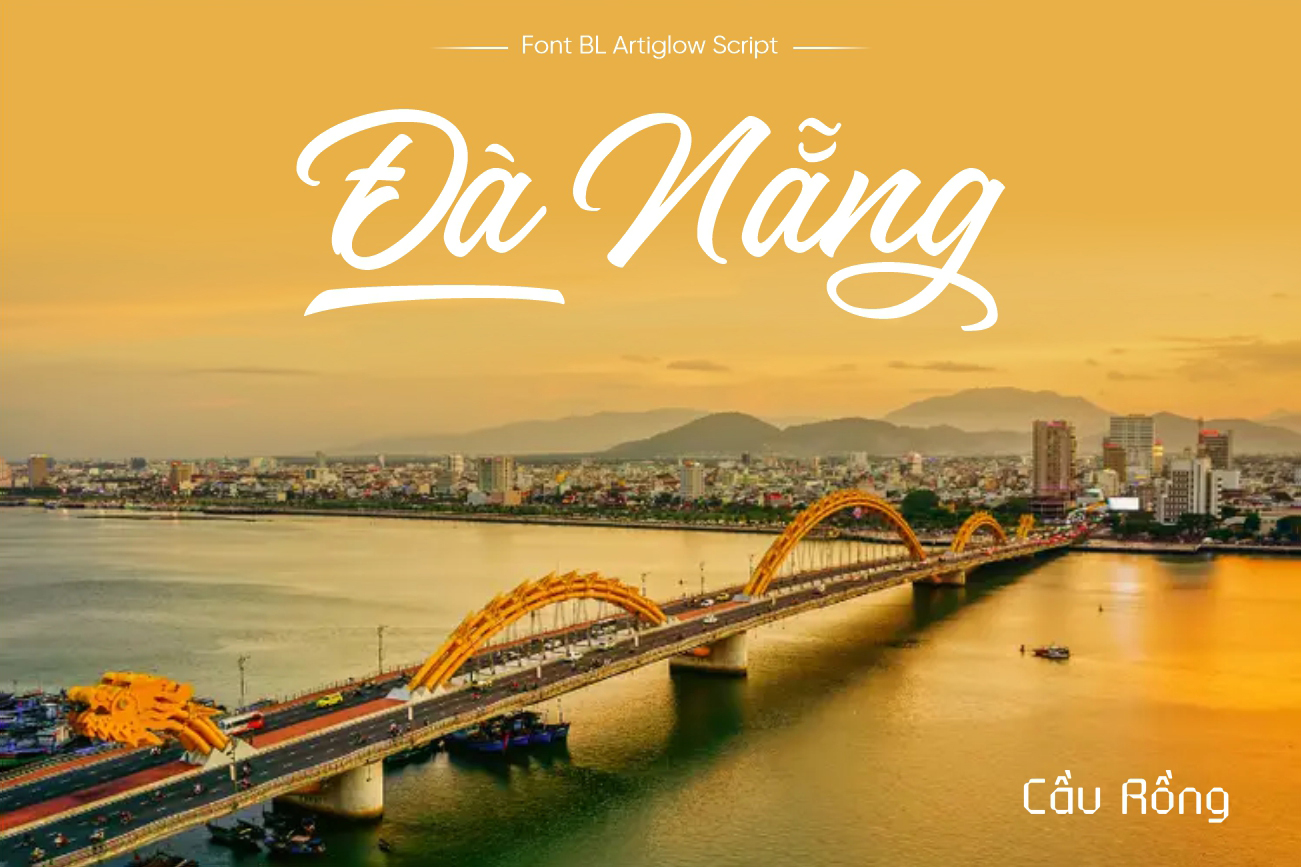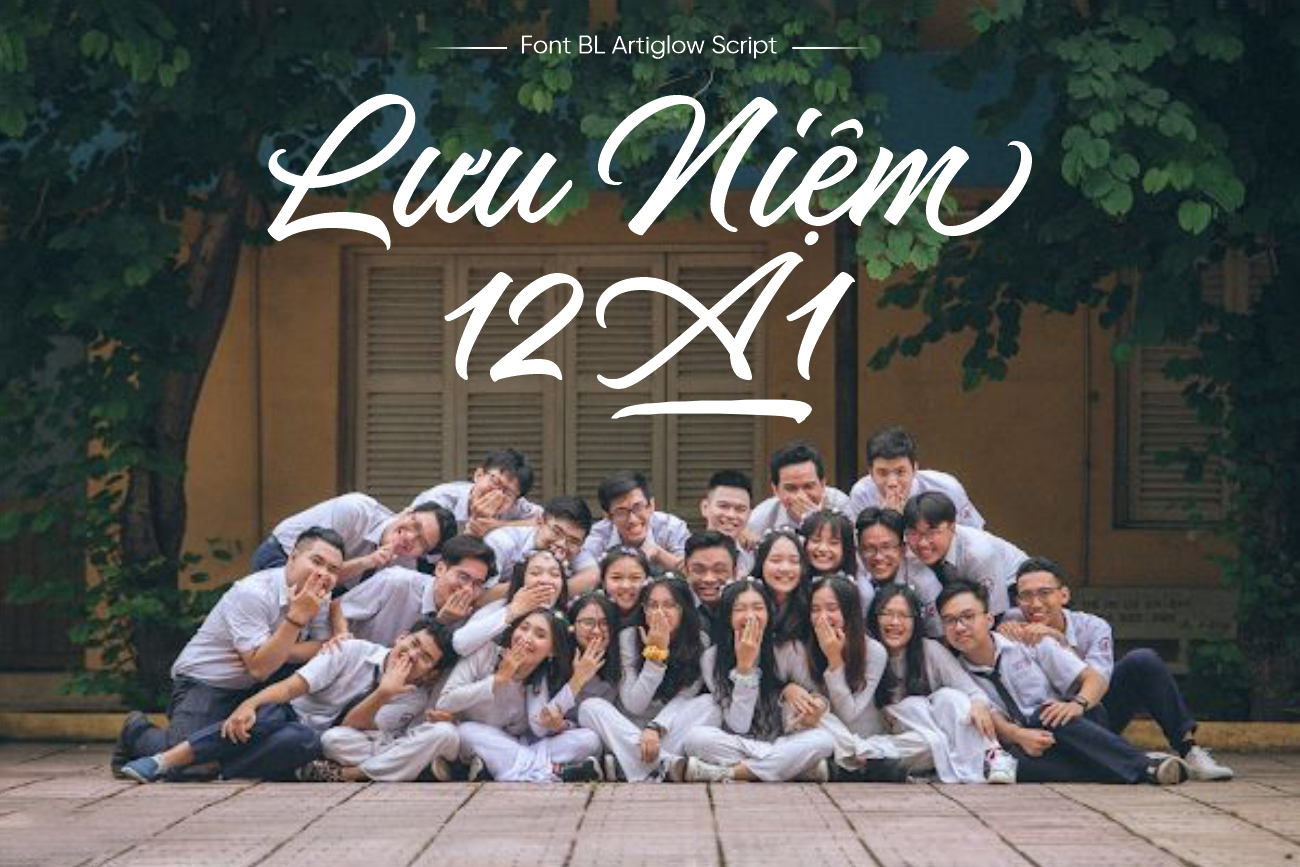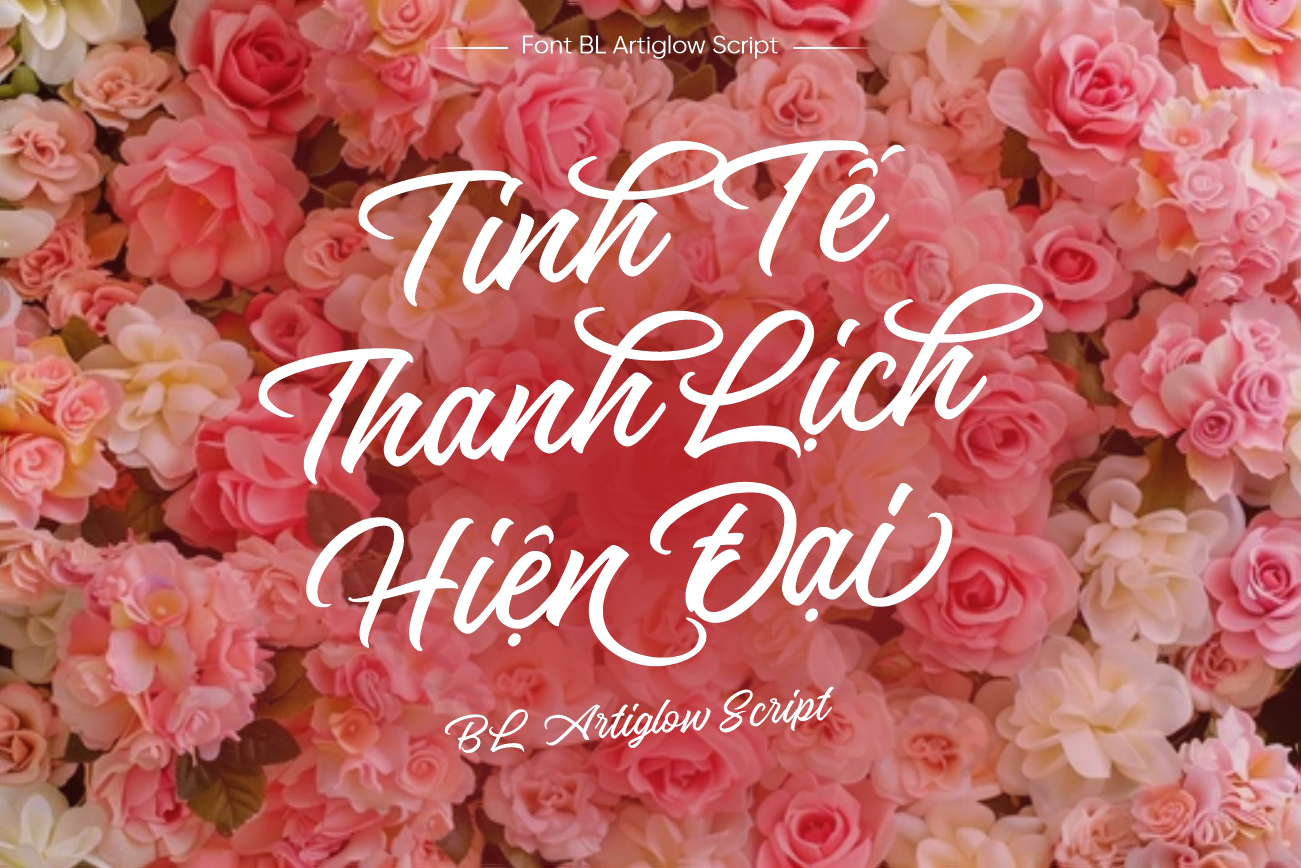
BL Artiglow Script - Font chữ cưới tinh tế, thanh lịch
BL Artiglow Script là phiên bản Việt hóa từ bộ font Artiglow Script do Joelmaker thiết kế, mang tinh thần nghệ thuật tinh tế và hiện đại, phù hợp với xu hướng thẩm mỹ đương đại. Ngay từ lần đầu tiếp xúc, bộ chữ tạo ấn tượng mạnh bởi phong cách mềm mại, bay bổng nhưng vẫn giữ được sự gọn gàng cần thiết, đúng chất của một font brush nét viết tay nghệ thuật tinh tế. Team BL đã thực hiện quá trình Việt hóa một cách cẩn trọng, tối ưu từng dấu tiếng Việt để các nét chữ liền mạch, hài hòa và không phá vỡ cấu trúc tổng thể, giúp BL Artiglow Script vừa đẹp mắt vừa dễ sử dụng trong nhiều ngữ cảnh thiết kế tại Việt Nam.
Về kiểu dáng, BL Artiglow Script sở hữu những đường nét uốn lượn tự nhiên, mô phỏng chuyển động của bút vẽ trên giấy, tạo nên cảm giác mềm mại và giàu cảm xúc. Tuy mang đặc trưng của font brush, bộ chữ không quá phóng khoáng hay thô ráp mà được tinh chỉnh để trở nên hiện đại, thanh lịch, phù hợp với các thiết kế yêu cầu sự tinh tế và sang trọng. Các nét chữ có độ dày mỏng linh hoạt, khoảng cách chữ được xử lý khéo léo giúp nội dung luôn dễ đọc, ngay cả khi sử dụng ở kích thước nhỏ. Chính sự cân bằng này giúp BL Artiglow Script phát huy tốt vai trò trong thiết kế logo, tiêu đề, poster, bao bì sản phẩm, thiệp mời, thiệp cưới hoặc các dự án truyền thông cần dấu ấn cảm xúc và tính nghệ thuật cao.
Nguồn gốc của Artiglow Script được xây dựng từ cảm hứng về chữ viết tay mang tính cá nhân, nơi mỗi ký tự đều thể hiện sự mềm mại và tinh thần sáng tạo tự do. Khi được Team BL Việt hóa và phát triển thành BL Artiglow Script, bộ font không chỉ giữ nguyên cá tính nghệ thuật vốn có mà còn trở nên thân thiện hơn với người dùng Việt nhờ khả năng hiển thị tiếng Việt mượt mà, chuẩn xác.
Nếu bạn đang tìm kiếm một bộ chữ kết hợp hài hòa giữa chất font brush nét viết tay nghệ thuật tinh tế với phong thái hiện đại, thanh lịch, BL Artiglow Script sẽ là lựa chọn lý tưởng để nâng tầm thẩm mỹ cho thiết kế, giúp từng dòng chữ trở nên cuốn hút, giàu cảm xúc và thể hiện rõ dấu ấn sáng tạo riêng.